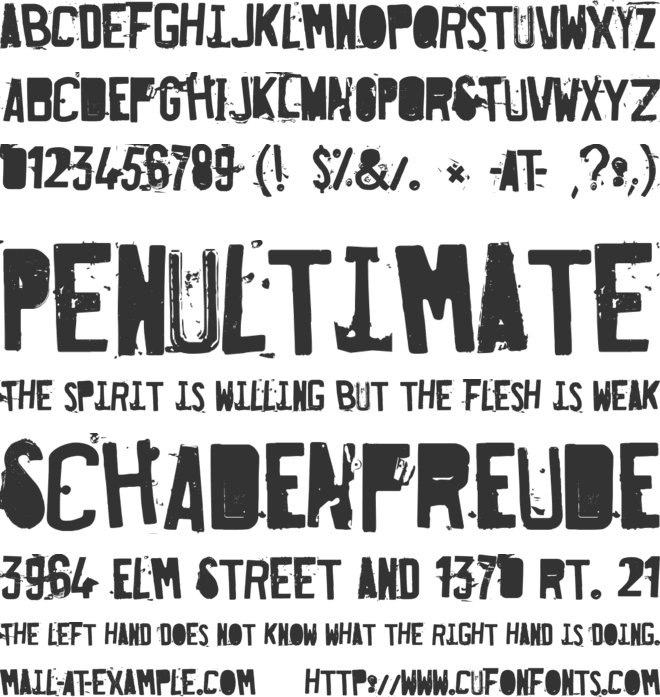
Fucked Plate Font
Merci d'avoir téléchargé Fucked Plate ! Créée à partir de photos de plaques d'immatriculations prises par moi-même, par Rodolphe (www.dafont.com) et par Farfadam(www.dafont.com). Cette fonte est un Abreuvware, vous pouvez l'utiliser gratuitement à but personnel et si vous êtes gentils vous pouvez m'envoyer une bière locale ! (n'hésitez pas à m'envoyer vos boulots faits avec ma police, ça m'interesse !). Merci de toujours laisser ce fichier Read_Me avec la police. Si vous voulez vous en servir à des fins commerciales, merci de me contacter par mail à  !
Hi, thanx for downloading Fucked Plate! Created from pictures of License Plates, taken by myself, by Rodolphe (www.dafont.com) and by Farfadam(www.dafont.com). This font is a Drinkware, you can use it for free for your personnal use only, and if you're nice you can send me a bottle of local beer (and don't hesitate to send me samples of your work, made with this font). Always keep this Read_me file with the font. If you want to use it for commercial purpose, please drop me a line at  !